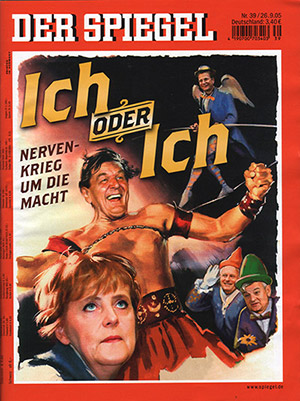
Schon mal mit Catchwords gespielt?Auf dem Titel des aktuellen Spiegel taucht eine typografische Rarität
auf, die man vor allem aus der Werbung kennt: ein Catchword. Dabei handelt es
sich um eine verzierte Wortmarke, die als Blickfang dient. Ein Fangwort, also.
![]() ![]() Titel des aktuellen SPIEGEL mit der Emigre-Schrift Brothers und einem Catchword Schriften mit Wortmarken: Underware Bello mit Words probesetzen ... Emigre Brothers mit Word Logos probesetzen ... Letteror Salmiak Catchwords angucken (PDF) und einkaufen ... FF Moderne Gothics mit Catchwords probesetzen ... (siehe auch: Sammelkarte Moderne Gothics ) Herausgegeben: Mo - September 26, 2005 at 06:14 nachm. | |